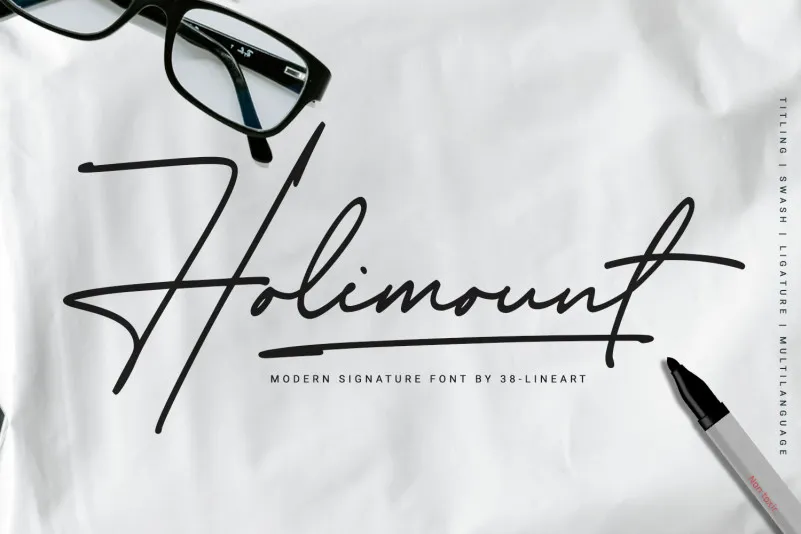
Holimount Handwritten Font – Download Grátis
A fonte Holimount Handwritten é uma criação cuidadosamente pensada para capturar a autenticidade do registro à mão. Ela foi projetada pelo designer 38.lineart, e cada traço convida aos olhos que se aventuram pela página, com movimentos delicadamente expressivos. Em nossa pesquisa inicial, notamos que esta fonte é frequentemente usada para assinaturas, uma característica muito apreciada por designers devido à sua personalidade única e aprimorada em cada traço. A Holimount Handwritten oferece um toque suave e versátil, se adequando tanto a textos informais quanto a designs de marca. Seu design envolvente permite que o designer construa elementos de texto com uma graça e naturalidade verdadeiramente autênticas, tornando-se uma fonte confiável para qualquer aplicação que busque um toque delicado em seu layout. Esta fonte representa muito além de apenas letras: ela é uma arte perfeita para os olhos sensíveis, oferecendo uma conexão ímpar entre o design e a natureza da escrita humana.
Designer: 38.lineart